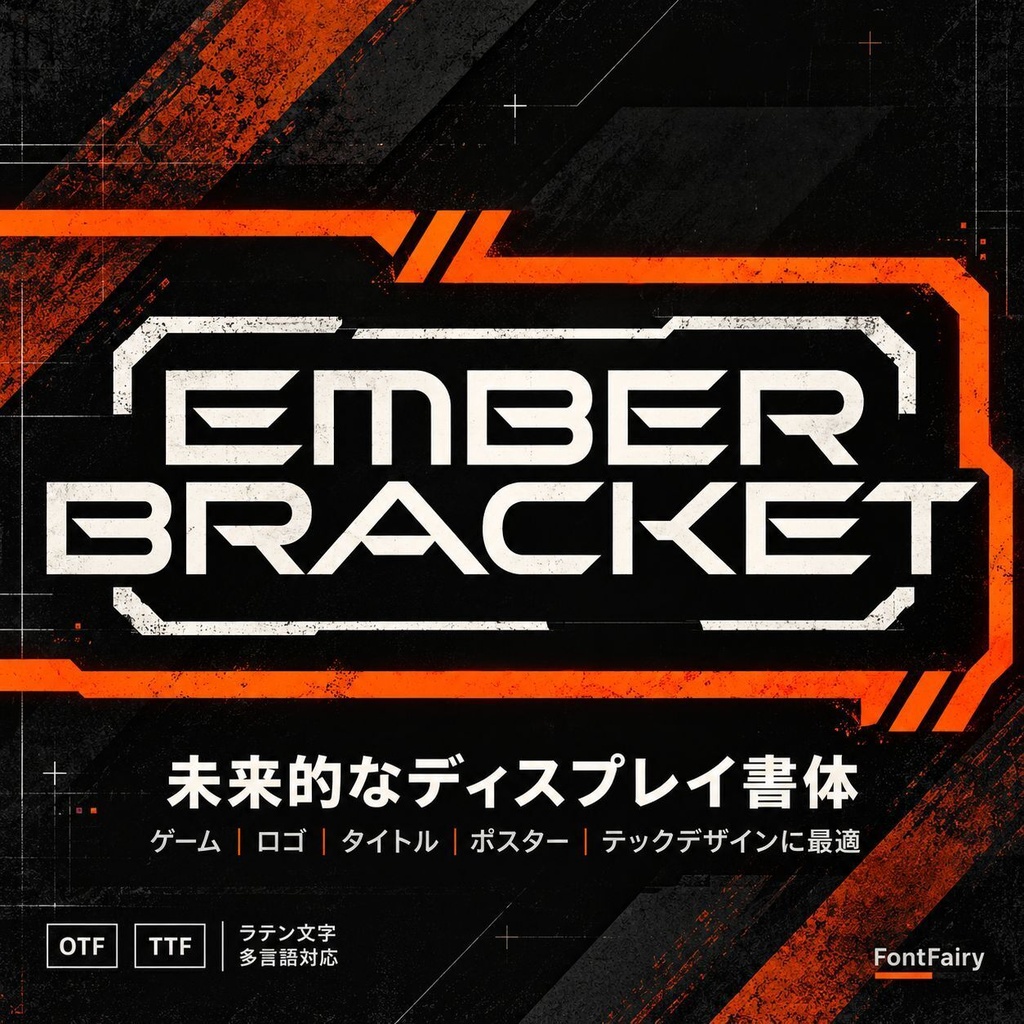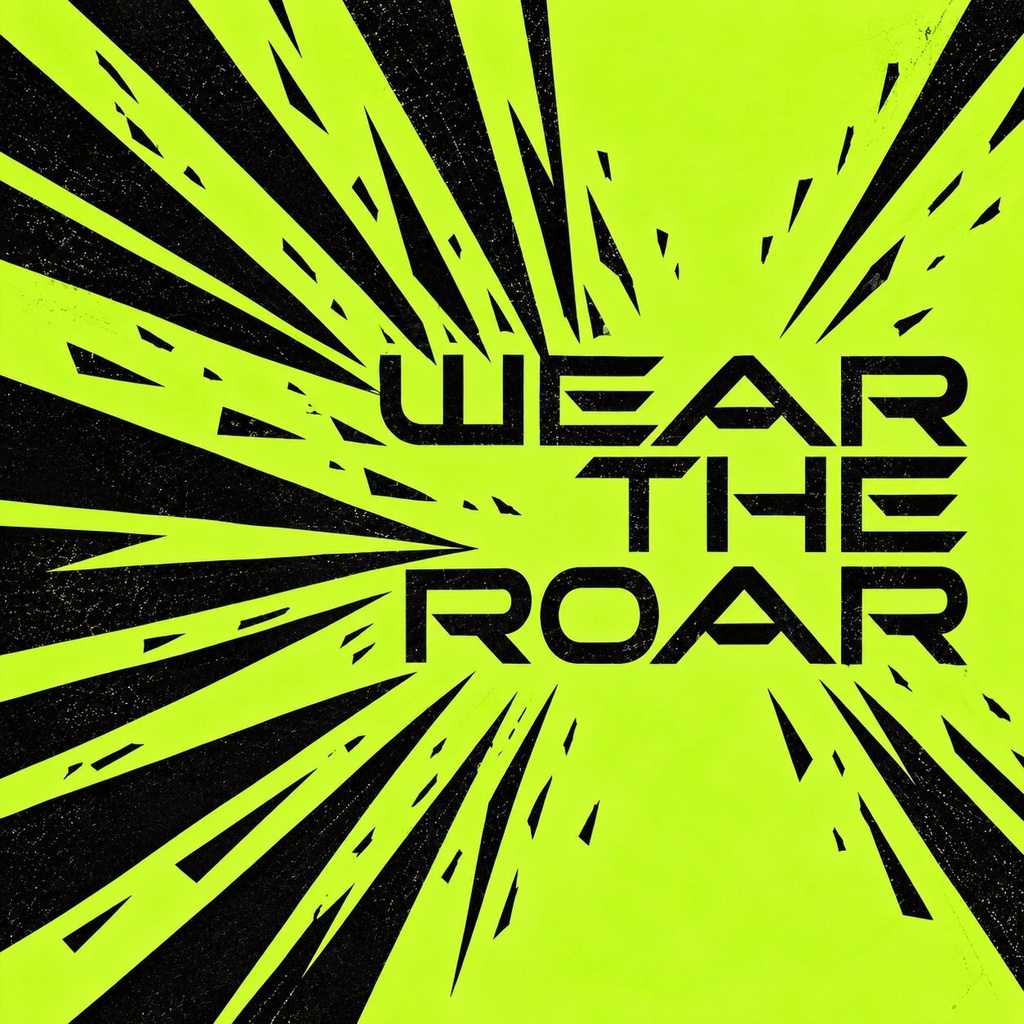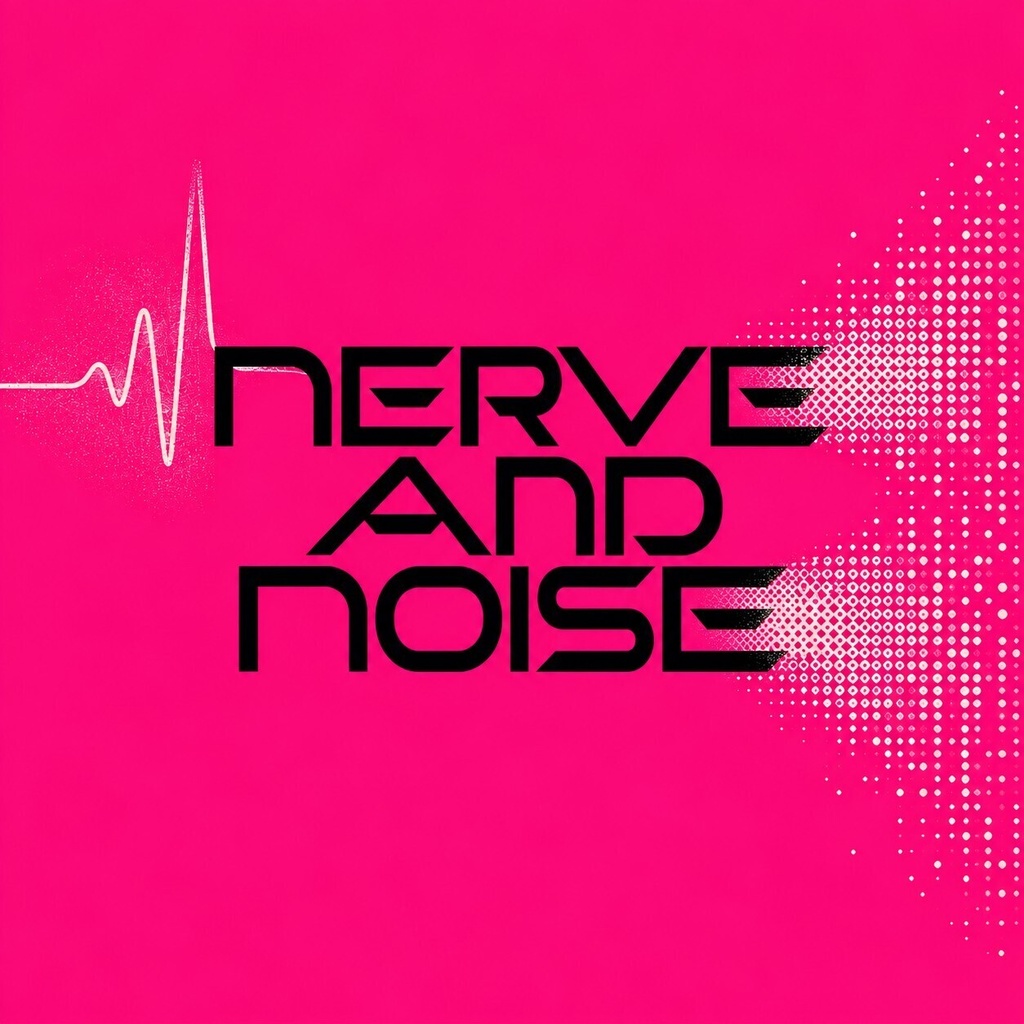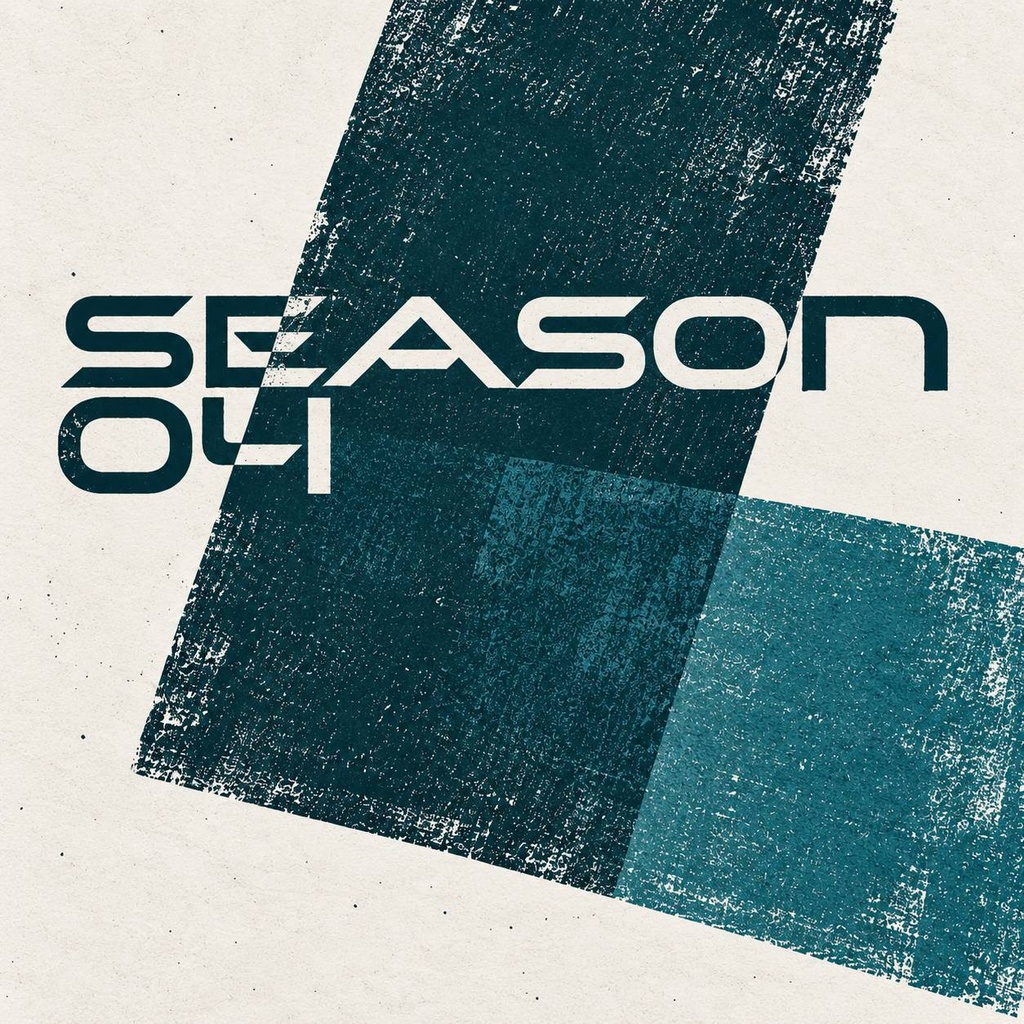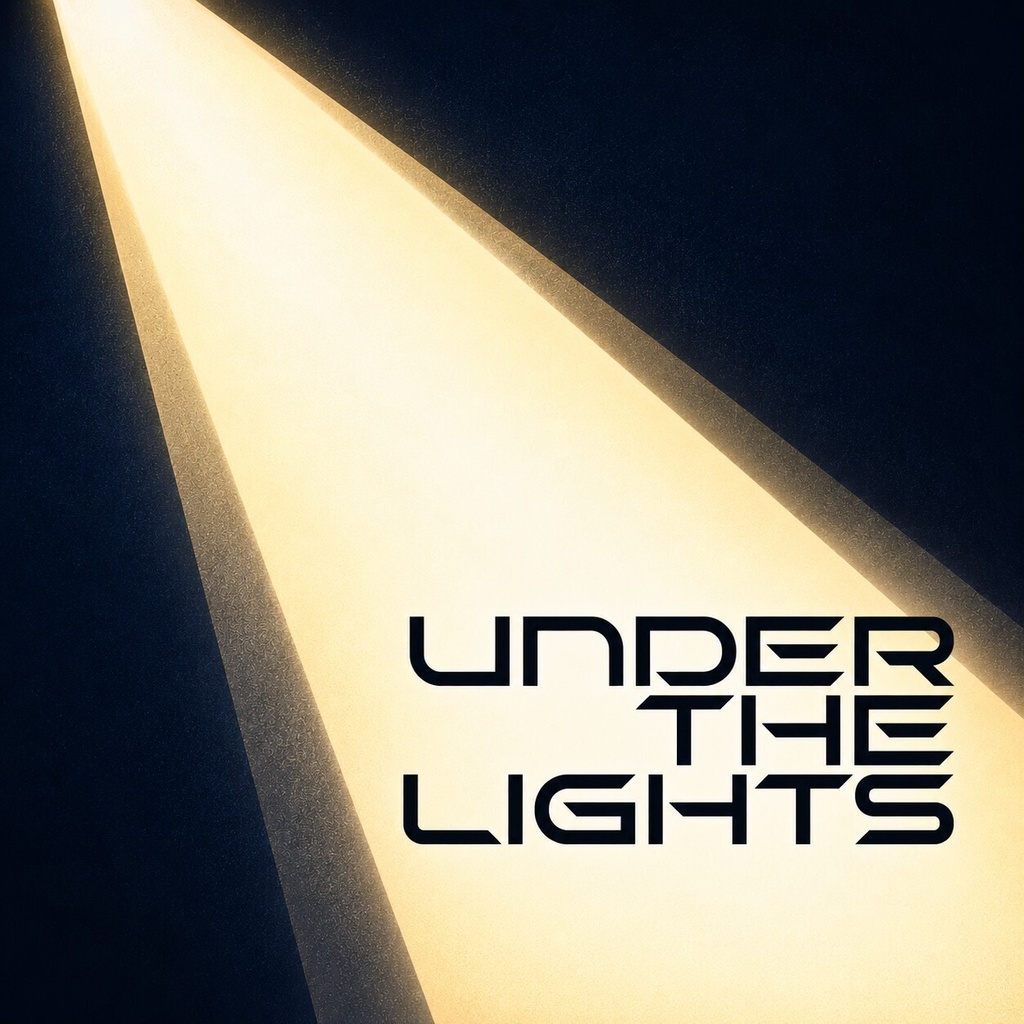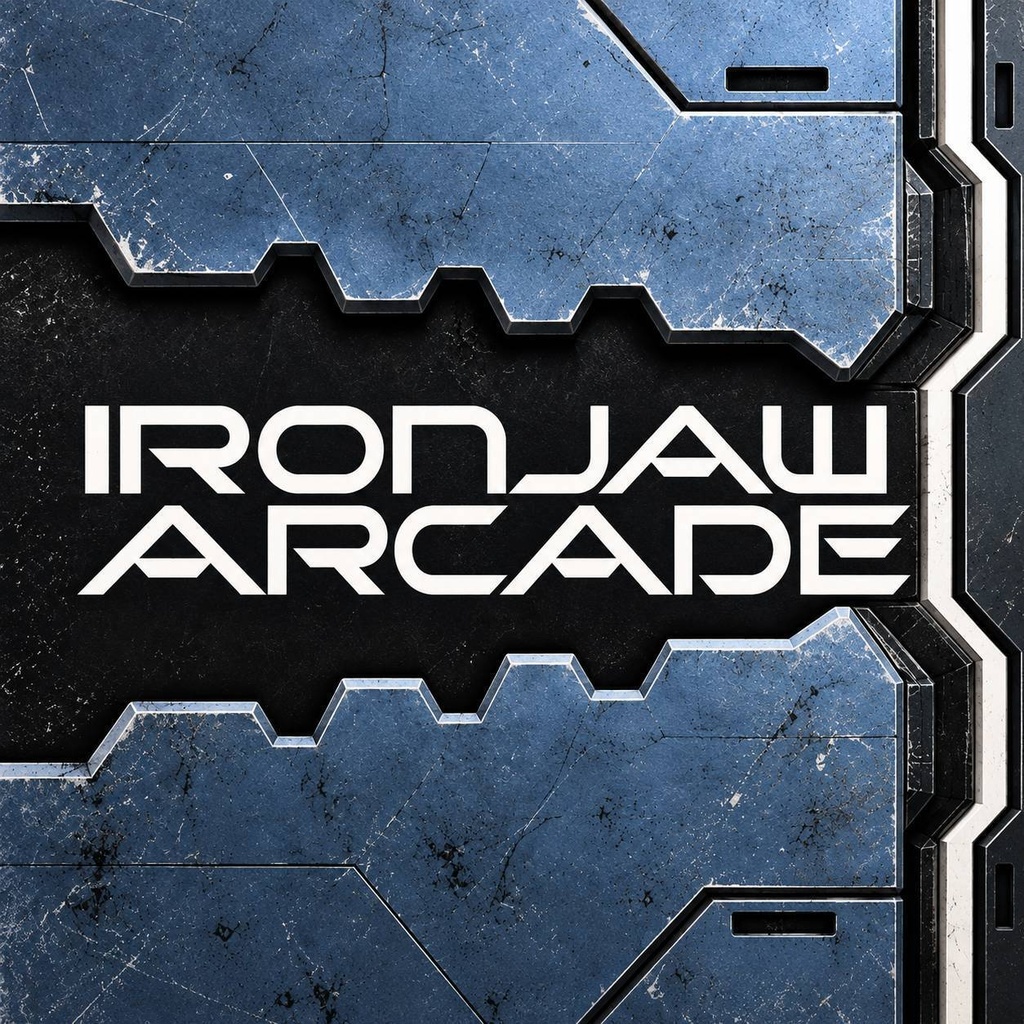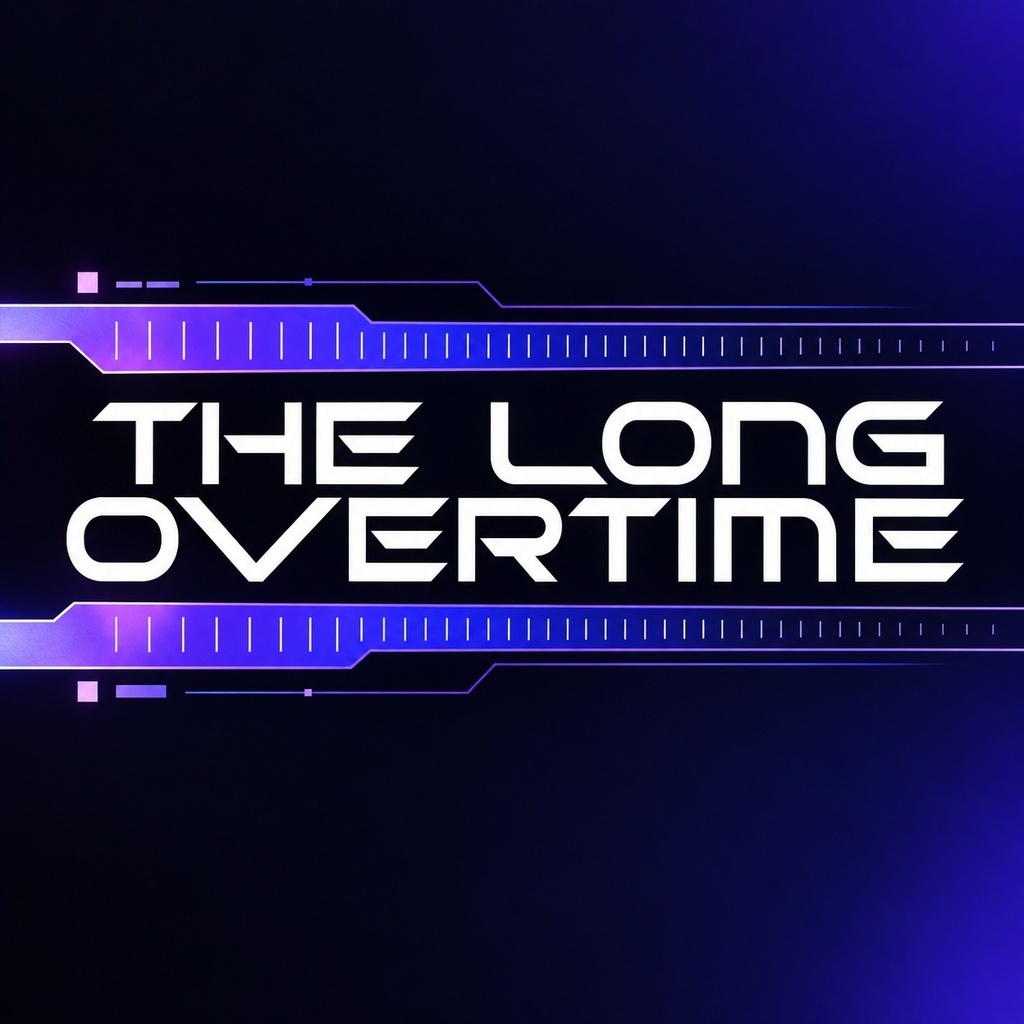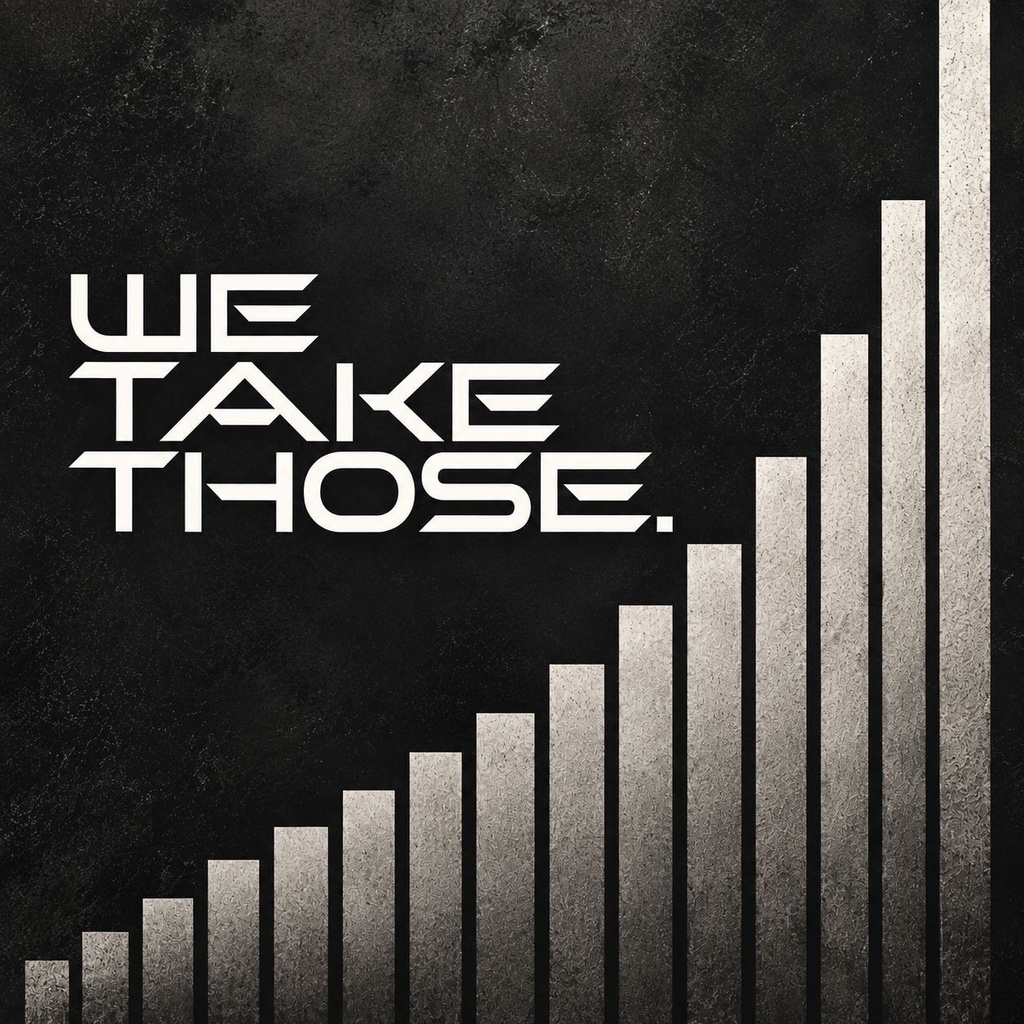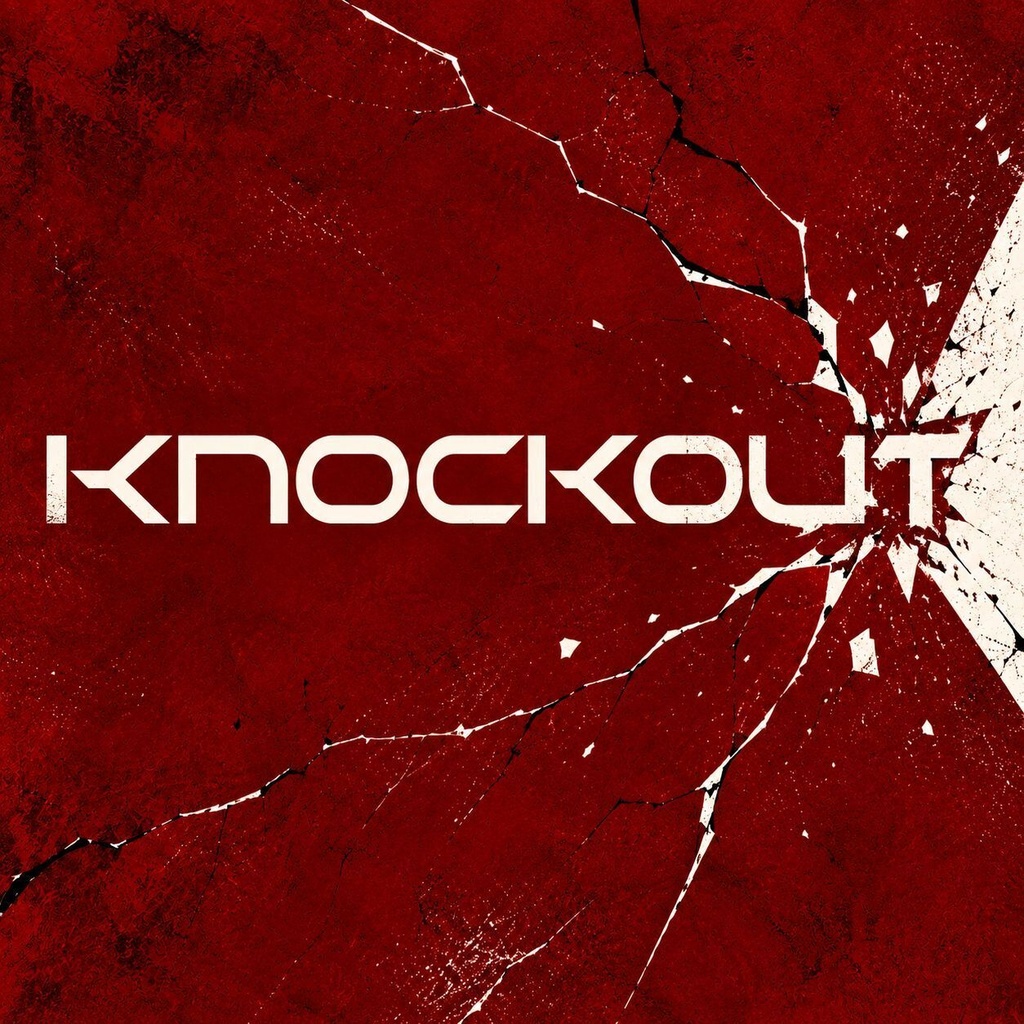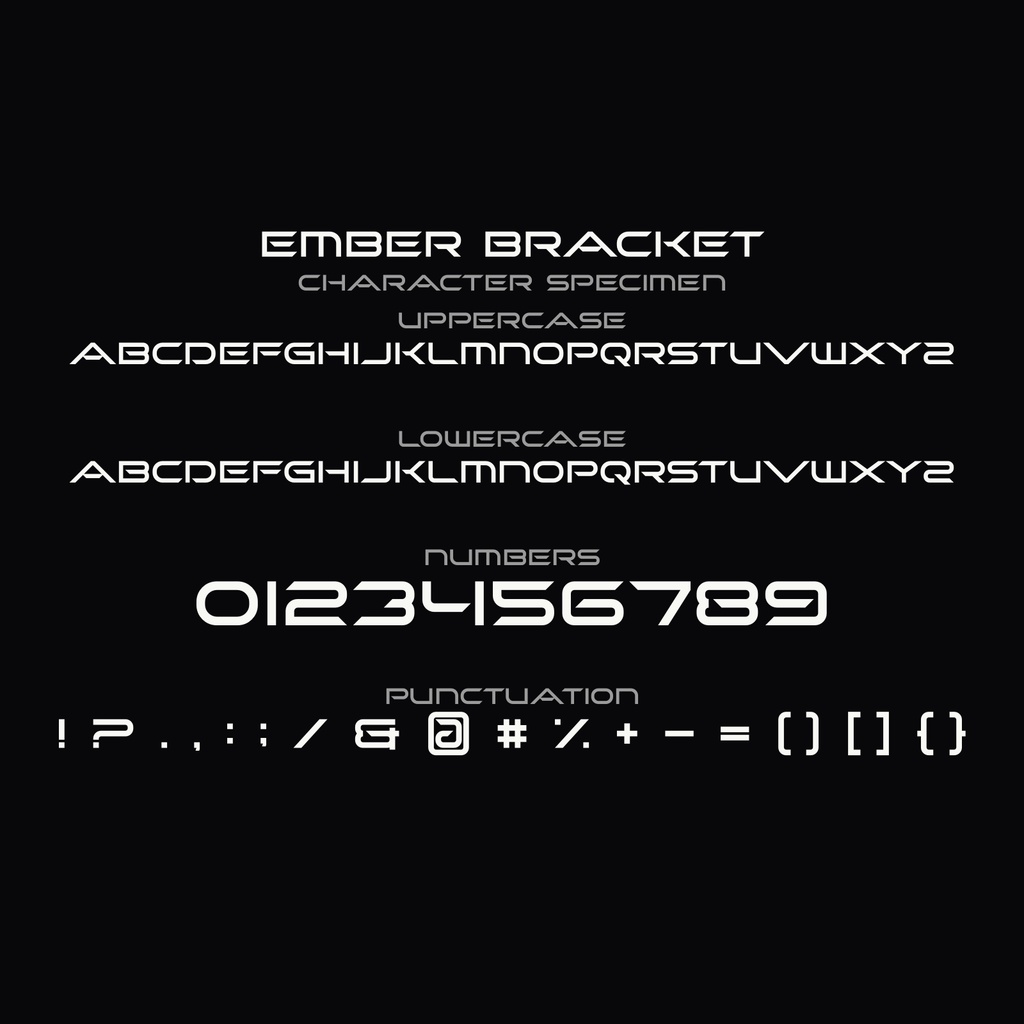
Ember Bracket【期間限定無料】| ボールド欧文ディスプレイフォント | ロゴ・見出し向け
【期間限定無料】Ember Bracket の無料デモを 2026年10月10日まで無料ダウンロードできます。 太く低い重心のカタチで短い言葉を画面いっぱいに広げる、欧文ディスプレイフォント Ember Bracket です。小文字を大文字と同じ高さで組めるため、一行の言葉そのものがロゴになるタイプ。ロゴ、チームマーク、トーナメントタイトル、Tシャツのプリント、配信やYouTubeのサムネイル、ポスターの見出しに合う書体です。 気に入ったらBOOTHで「いいね」・お気に入り登録をお願いします。 ダウンロードできるのは期間中の無料デモのみ、¥0 です。期間終了後は無料デモの提供が終わります。 商用利用・クライアント納品・広告・販売グッズには、有償のフルバージョン(FontFairy Commercial Font License 付き)をお選びください。 ■ 収録内容 ・Ember Bracket 1書体(Regular の 1 ウェイトのみ。イタリック・代替グリフなし) ・101グリフ/160文字マッピング(1000 units-per-em) ・GPOS カーニング内蔵。数字と句読点も本文と同じ高さで組めます ■ 対応文字 ・大文字 A–Z、小文字 a–z ・数字 0–9、句読点・記号・引用符 ‘ ’ “ ” ・アクセント付き入力は、ベースの文字として表示されます ・日本語・キリル文字・ギリシャ文字には対応していません ■ 用途 ロゴ、チームマーク、ジャージのネームプレート、トーナメントタイトル、eスポーツの配信グラフィック、サムネイル、バナー、ポスター、フライヤー、放送タイトル、パッケージ、ステッカー、同人誌の表紙、見出し、タイポグラフィ、SNS投稿 ■ 形式 ・EmberBracket-Regular.otf(OpenType) ・EmberBracket-Regular.ttf(TrueType) ・EmberBracket-Regular.woff(ウェブ用) ・EmberBracket-Regular.woff2(ウェブ用・圧縮版) ■ 対応環境 ・OTF/TTF は一般的なデザイン・DTP・画像編集ソフトでご利用いただけます ・WOFF/WOFF2 はウェブページの文字組みにご利用いただけます ・動作は OS とソフトのバージョンによって異なります ■ 利用許諾 ・無料デモ(期間中 ¥0):ご自身の個人的な作品、学習、練習、私的な投稿にお使いいただけます。商用利用・クライアント納品・広告・販売グッズには使用できません ・フルバージョン:FontFairy Commercial Font License に基づく商用利用権を含む有償版です。営利・納品・広告・ブランド・収益化・グッズの用途はこちらです ・フォントデータの取り扱いは FontFairy Commercial Font License に従います ■ お問い合わせ インストールや使用方法で不明な点がありましたら、メッセージでお知らせください。ご意見・ご要望もお気軽にどうぞ。 Copyright (c) 2026 FontFairy. Ember Bracket is a trademark of FontFairy.